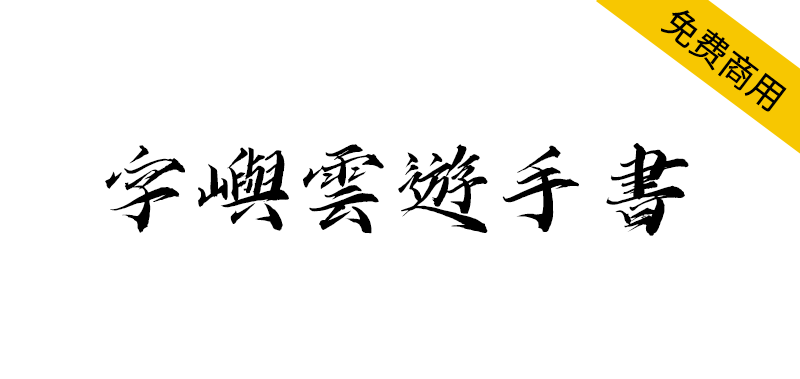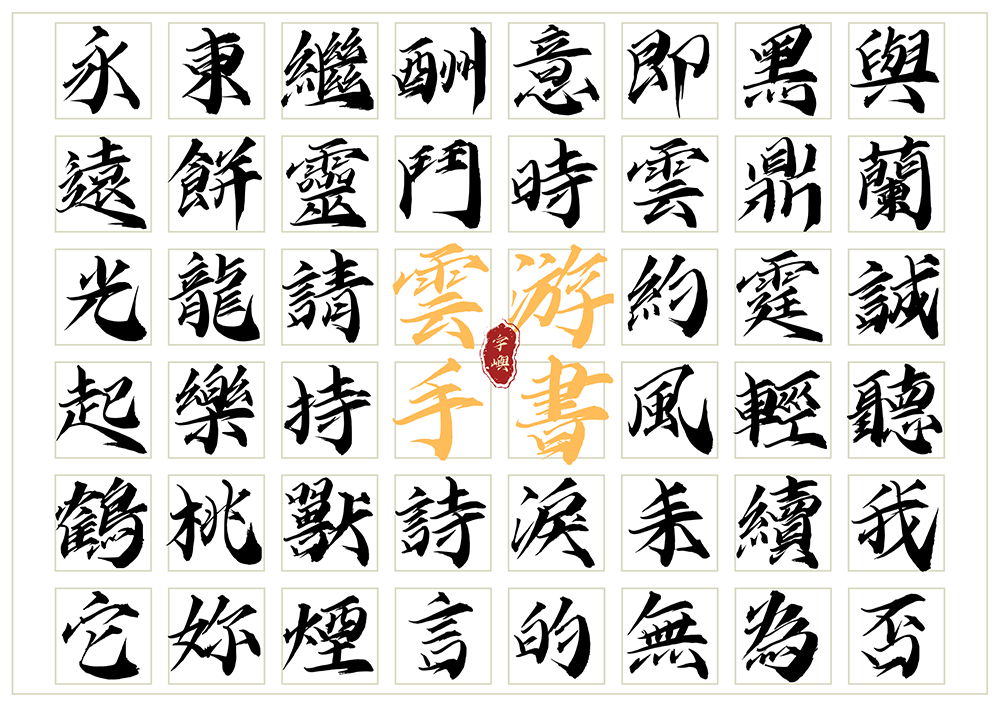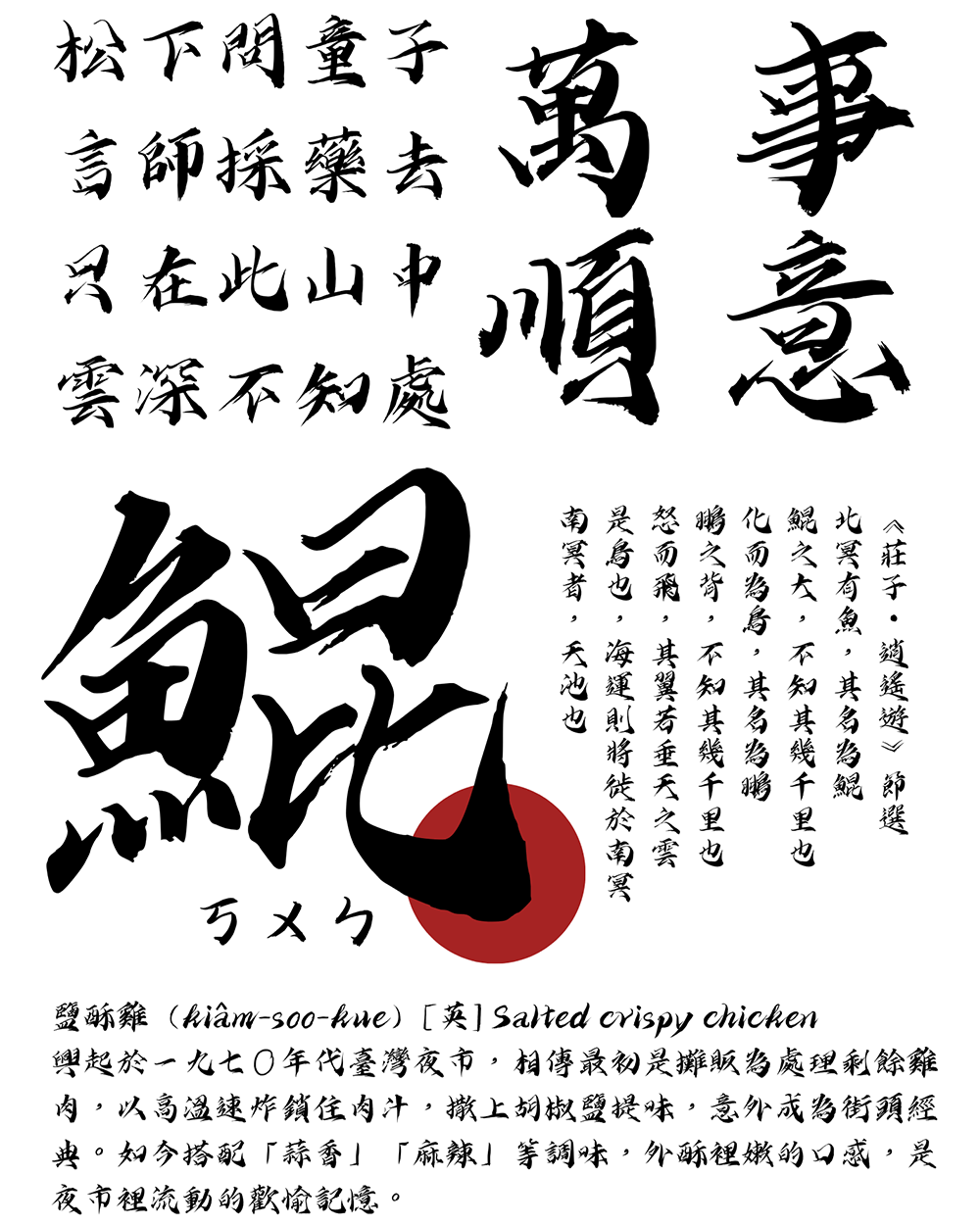
字屿云游手书是一款以毛笔字风格为基底,更为强调字体笔画的曲折收放变化的创意手书字体。以台语常用标准汉字为标准,参考jf7000字集,包括注音符号、欧文字符、阿拉伯数字和标点符号,总字符约7640字以上。
字屿云游手书整体字势开合揖让得宜,腾挪转折间,不致过于纤秀婉约,婉转中犹见铿锵力度,锋芒尽显。透过局部形变与笔势外拓,叠加出整体气势,兼顾阴柔与阳刚、含蓄与强劲之美。露锋用笔贯穿字体始终,结体紧致,大量曲线更强化字势动感与字形张力,恰似流云萦绕剑锋,飘逸中蕴藏锐劲。
我们希望这款字有无限的可能性:国潮文创(手帐封面题字、刺绣吊饰文字)、茶饮与伴手礼(珍珠奶茶杯身题字、凤梨酥礼盒侧边文案)、出版领域(乡土神话故事集、山林散文选的封面与章节标题)、影视动画(仙侠剧开场片名、庙宇场景牌匾题字)、户外广告(古迹园区导览牌、文创商圈灯箱)、传统服饰(庙会常见的服饰刺绣文字、改良旗袍腰带印字)、文博展览(特展海报、老街文物说明卡)、品牌识别(中药行招牌、台式茶馆)、工艺饰品(陶瓷茶具底款、珊瑚吊坠刻字)